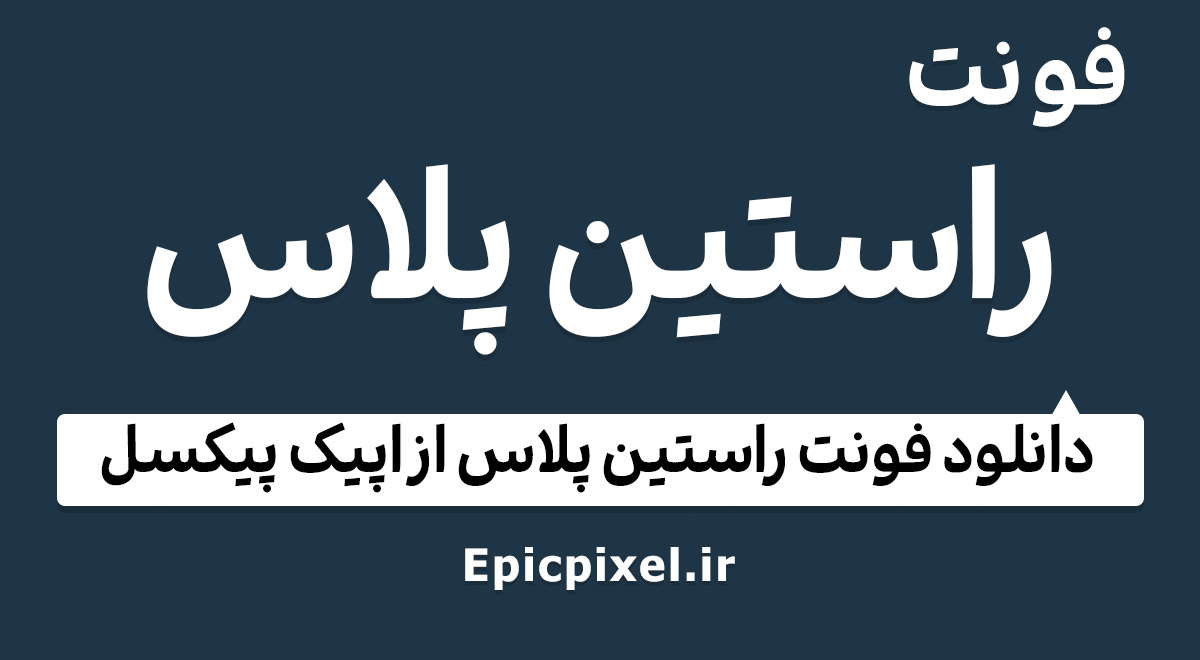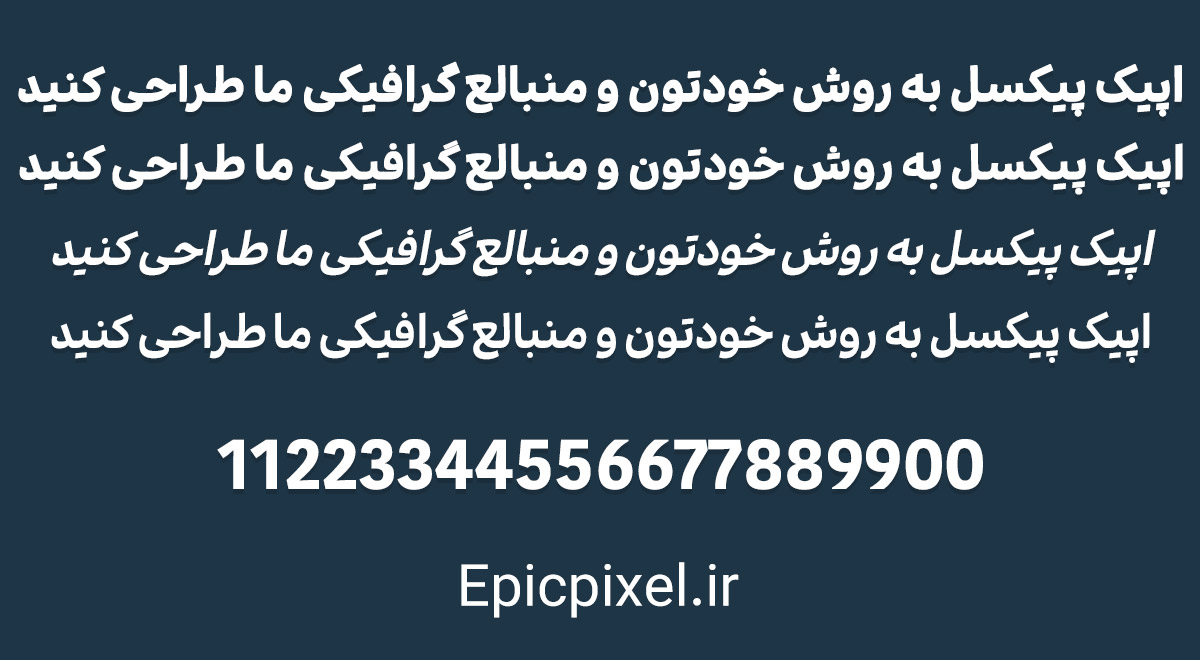
3 فونت راستین پلاس فارسی Rastin Plus
فونت راستین پلاس: قلم هوشمند برای طراحی های حرفه ای
اگر به دنبال فونت فارسی ای هستید که ترکیبی از زیبایی و کارایی باشد، فونت راستین پلاس گزینه ای مناسب برای شماست. این قلم هوشمند با طراحی پویا و جدی، بهینه سازی شده تا در انواع پروژه های گرافیکی و وب، حرفه ای و بدون تداخل نمایش داده شود .
یکی از ویژگیهای برجسته آن کرنینگ متعادل است که خوانایی متن را در حروف ابتدایی و میانه جمله ای بهبود میبخشد . همچنین، نقاط حروف به طور اتوماتیک جابه جا میشوند تا از هم پوشانی ناخواسته جلوگیری کنند . این مجموعه شامل سه استایل متنوع است که انعطاف پذیری را برای طراحان افزایش میدهد. از جمله این استایلها میتوان به راستین پلاس دایره و راستین پلاس لاین اشاره کرد که هر کدام شخصیت منحصر بفردی به طرحها می بخشند. فونت راستین پلاس با فرمت TTF و OTF عرضه میشود و سازگاری کامل با نرم افزارهای گرافیکی و وب را دارد .